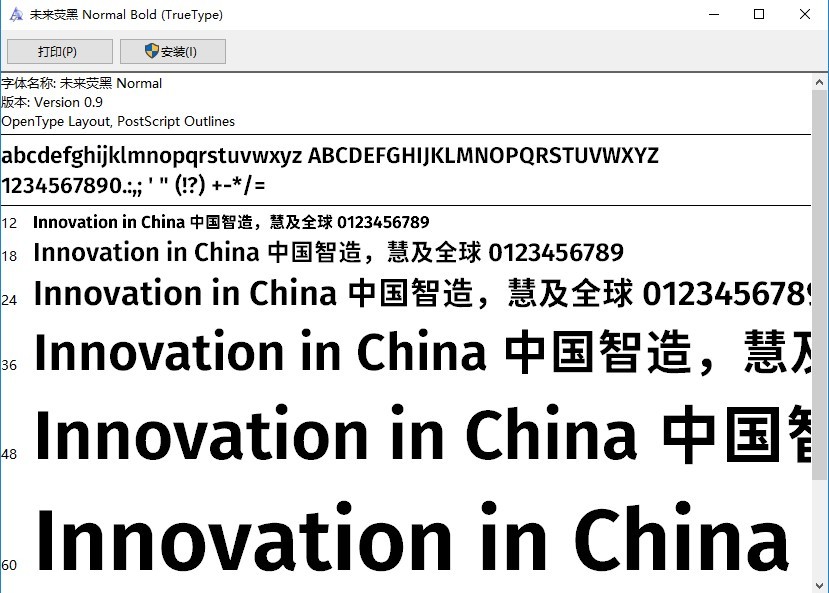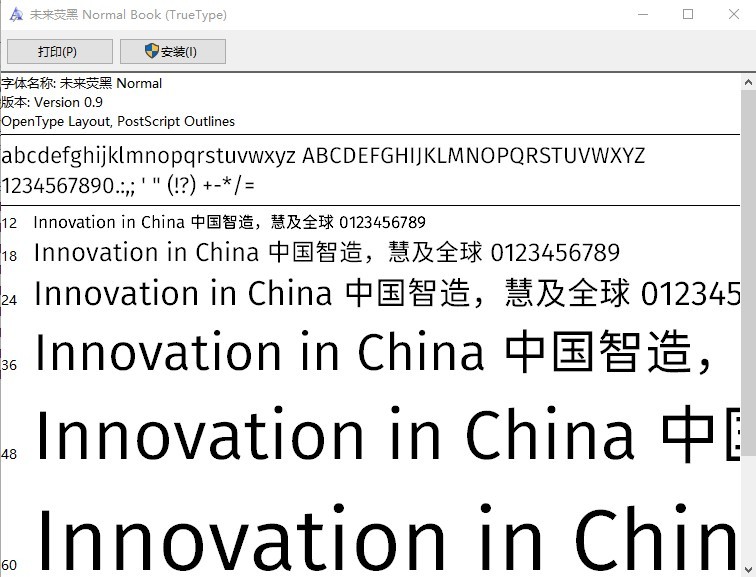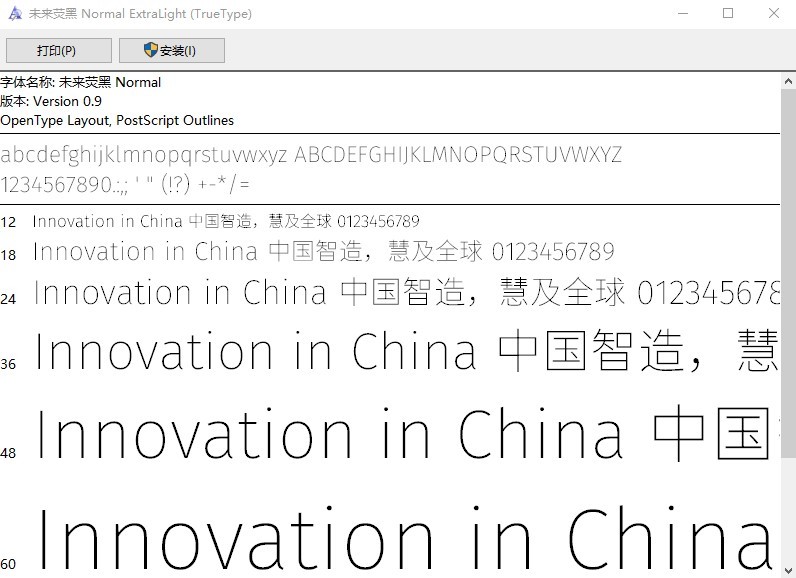
未來(lái)熒黑字體免費(fèi)商用版是一款好用設(shè)計(jì)字體,屬于黑體類(lèi)型,看起來(lái)比較簡(jiǎn)潔工整,同時(shí)顯得比較干練輕快,具有現(xiàn)代特色風(fēng)格,適用范圍十分廣泛,可以運(yùn)用在各種設(shè)計(jì)領(lǐng)域場(chǎng)合,還可以支持多種語(yǔ)言,方便又好用!
未來(lái)銀黑是一個(gè)基于思源黑體、firasans和raleway的開(kāi)源字體項(xiàng)目,支持簡(jiǎn)體中文、繁體中文和日文;思源黑體7字重?cái)U(kuò)展為9字重,提供寬度系列,全家44字體。與思源黑體相比,未來(lái)銀黑的造型更加簡(jiǎn)潔現(xiàn)代,布局效果清新輕快。未來(lái)銀黑的中宮和字面更加收斂,重心在字重之間重新配置;筆畫(huà)細(xì)節(jié)處理得更加干練、簡(jiǎn)潔、直白。您可以下載樣品來(lái)預(yù)覽未來(lái)銀黑的設(shè)計(jì)。
1、字體工整簡(jiǎn)潔,具有強(qiáng)烈的視覺(jué)沖擊力
2、未來(lái)熒黑的實(shí)現(xiàn)介于參數(shù)化與輪廓濾鏡,使用了圖像處理算法對(duì)字形建模
3、適應(yīng)于報(bào)紙和雜志和書(shū)籍中常用字體, 海報(bào)、個(gè)性促進(jìn)品牌標(biāo)志設(shè)計(jì)、字體設(shè)計(jì)、等環(huán)境使用
q:支持韓文嗎?
a:不支持。以后的版本可能會(huì)提供韓文支持。
q:這是可變字體嗎?
a:不是。未來(lái)熒黑是通過(guò)在思源黑體上形變來(lái)改變字形形態(tài)、拓展家族的,思源黑體沒(méi)有發(fā)布可變版本,我們也無(wú)從恢復(fù)其母版數(shù)據(jù)。但是不排除在未來(lái)有封裝成有寬度軸的可變字體的可能性。你可以玩一玩我們的 demo ,來(lái)更加直觀(guān)地看到形變是如何實(shí)現(xiàn)的。